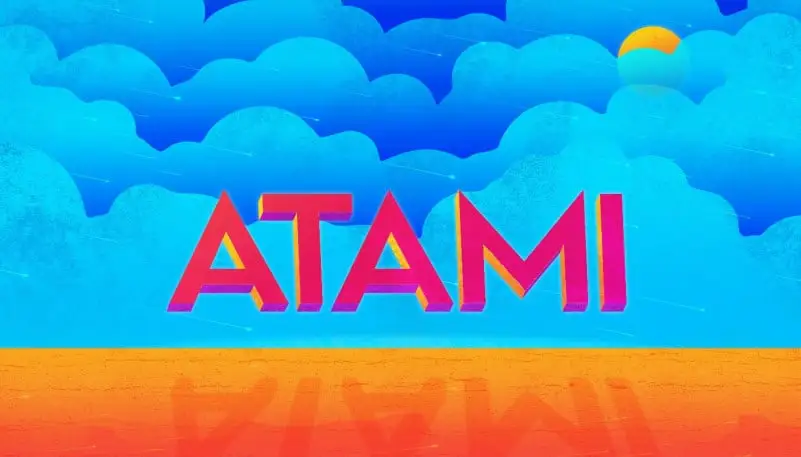
Atami Sans Serif Font – Download Grátis
Atami Sans Serif é uma elegante escolha para estilos visuais modernos que valorizam simplicidade e agilidade. Com suas letras maiúsculas, números e sinais de pontuação apresentando os mesmos atributos dos minúsculos, a fonte oferece flexibilidade na criação de elementos tipográficos como logomarcas, marcas de texto e headlines. Suas proporções normais garantem que seja usável tanto para o tipo de impressão quanto em designs digitais. Esta fonte é uma ótima escolha para quem procura uma mistura de simplicidade e força, dando vida a criações visuais com um ar moderno e contemporâneo.